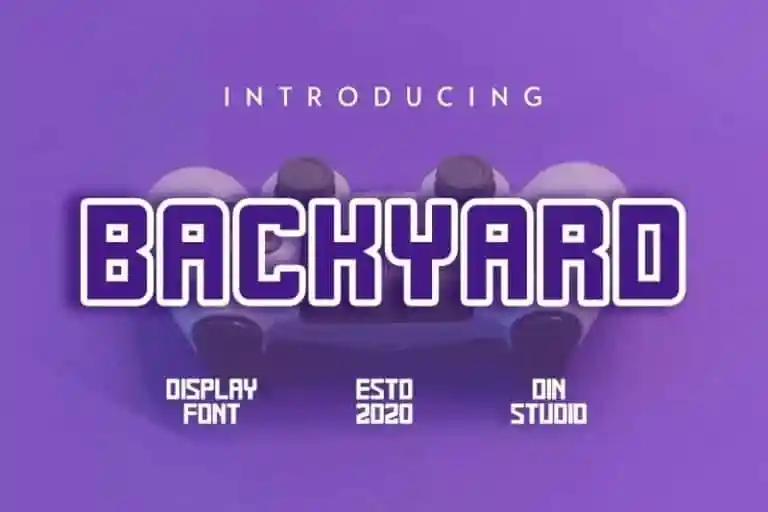
Backyard Display Font é uma elegante tipografia para uso em display projetada inspirada em blocos de fontes e objetos relacionados ao esporte. Esta fonte fascinante, com um estilo alegre, se destaca para várias aplicações e promoções diferentes. É perfeita para ser usada no seu site, na identidade visual da sua empresa, nas banners do Pinterest, em produtos impressos e muito mais! Acompanhe essas possibilidades criativas ao usar Backyard Display Font em vários formatos de mídia.